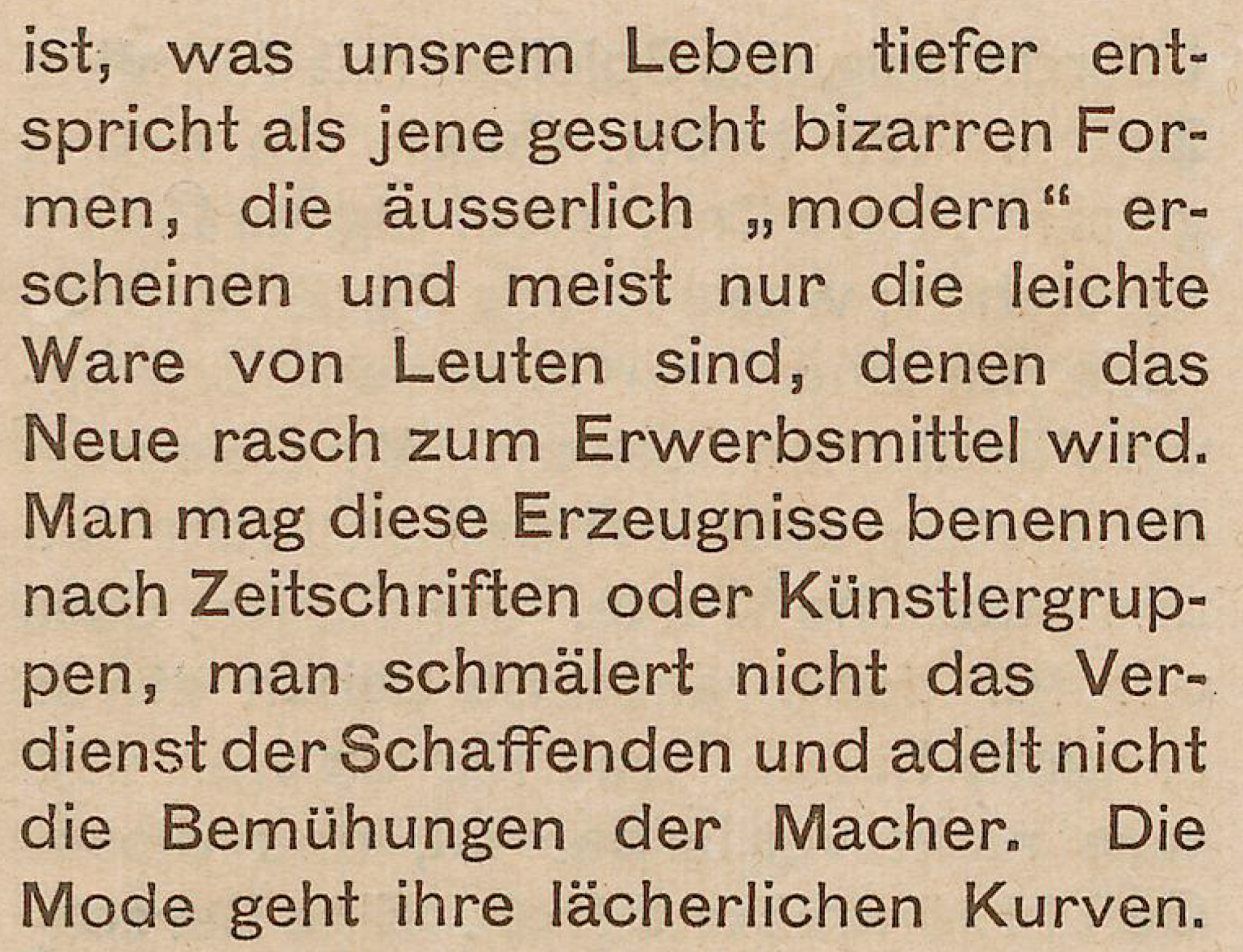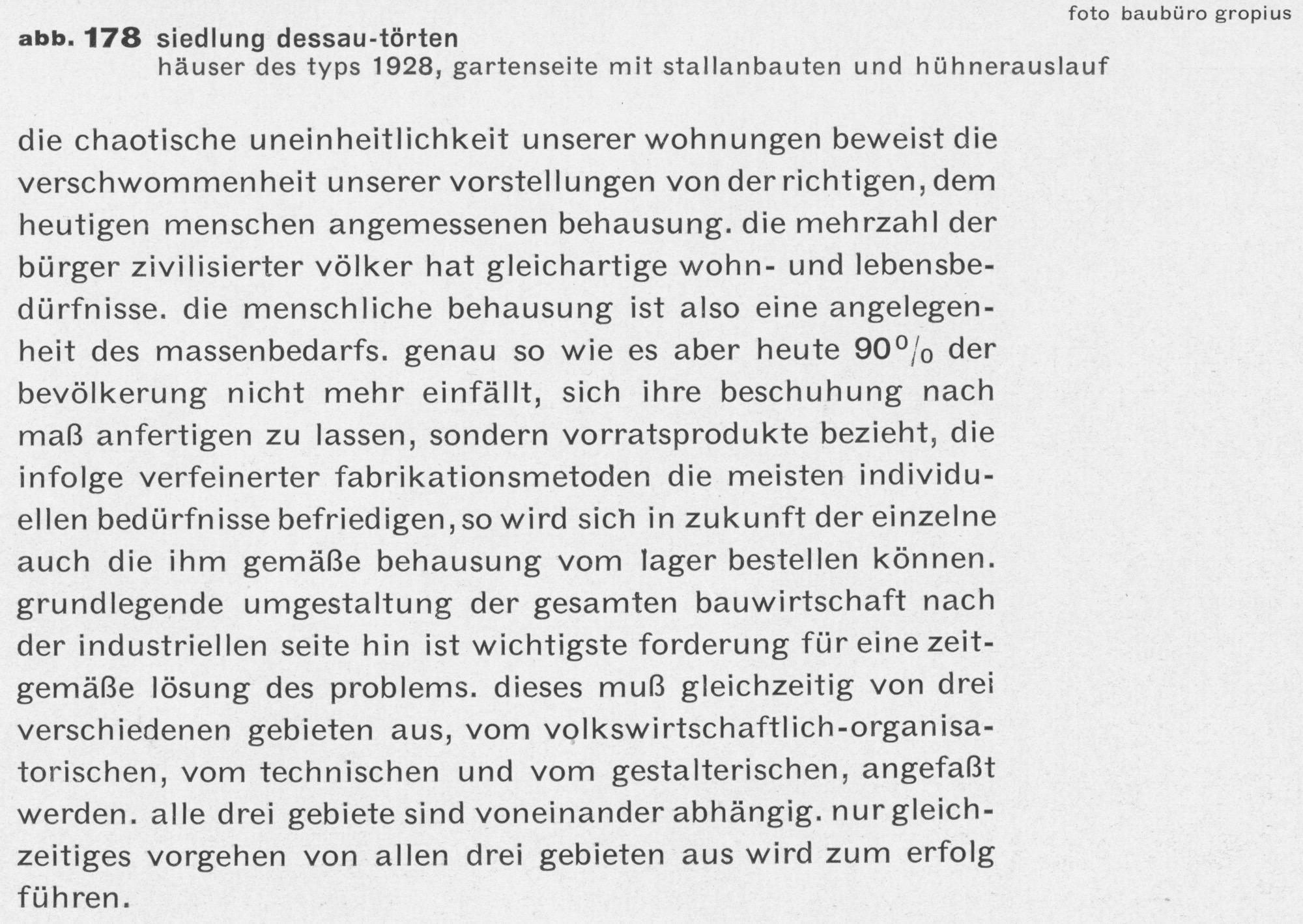
Schrift aus Bauhausbücher 12, 1930
Kann mir jemand sagen was dies für eine Grundschrift ist? und ob diese evtl. digitalisiert wurde?
ist aus dem Buch: «Bauhausbücher 12: Walter Gropius, bauhausbauten Dessau»
gedruckt: 1930
erschienen im Verlag: Albert Langen Verlag München
druck: Hesse & Becker, Leipzig
Ich kann leider nicht sagen welche Schrift es ist aber es ist mit Sicherheit nicht die Akzidenz Grotesk. Allein das »g« passt schon nicht – von den Strichstärkenunterschieden bei etlichen anderen Lettern (a, b, c, …) ganz zu schweigen.
Diese Schrift war eine sehr gängige »anonyme« Schrift zu der Zeit. Die wurde vermutlich in den 1870er Jahren aus Großbritannien importiert. Bei mehreren deutschen Schriftgießereien hieß die Schrift Breite Grotesk. Aber nicht alle Schriften aus der Zeit, die Breite Grotesk hießen, ließen sich auf diesem Entwurf zurückgehen. In etwas zwei Stunden poste ich eine Liste von den Schriftgießereien, die diese Schriften im Angebot hatten. Vielleicht könntet ihr dann eine Probe im Netz finden. Eine digitale Version dieses Entwurfs (anders als die andere breite Groteskschriften von Schelter & Giesecke) gibt es leider nicht.
Eine digitale Version dieses Entwurfs … gibt es leider nicht.
Schade, die hat nämlich wirklich Charme.
Die Schrift aus dem Bauhaus-Buch ist dieselbe (oder eine nahezu identische Kopie für eine Satzmaschine) wie die Schrift, in dem Peter Behrens’ Buch Feste des Lebens und der Kunst: eine Betrachtung des Theaters als höchsten Kultursymbols (Darmstadt, 1900). Anbei ein weniger-tolles Foto von ein paar Zeilen aus Behrens’ Buch.
Meine Vermutung ist, dass Ludwig & Mayer in Frankfurt die erste deutsche Gießerei war, die diese Schrift in Deutschland anbot (sie entwarf die jedoch nicht). Sie nannte die Schrift Breite Grotesque. Wilhelm Woellmer’s Schriftgießerei in Berlin hatte das Design auch (unter der Name Breite Grotesk). Woellmer war jedoch aber nicht die Firma, die sie ursprünglich herstellte. Wie oben geschrieben vermute ich, dass die Schrift in Großbritannien »geboren« worden ist; deutsche Gießereien hätten Matrizen davon bekommen, entweder in dem sie Matrizen von denen gekauft haben oder sie über die Galvanoplastik geklauten. Es kann sein, dass die genaue Situation von Firma zu Firma sich unterschied.
Als Quelle Tippe ich auf Miller & Richard (also ihre Grotesque, No. 1), wobei die Gothic No. 9 von der Cincinnati Type Foundry in den USA sehr ähnlich aussieht und ich habe keinen grundlegenden Vergleich gemacht. Vielleicht kam sie von Cincinnati an Miller & Richard oder anders herum.
Woellmer machten sogar weitere Schriften, die im selben Designstil waren. Also bauten sie daraus eine kleine »Familie« mit halbfett, eine schattierte Version, die schattierte Version für dem zweifarbigen Druck usw. (einige Bilder davon kommen in meinem Vortrag hier auf; ansonsten hat Ralf vielleicht Proben von diesen Schriften in Weimar).
Ansonsten in Deutschland boten Brüder Butter in Dresden sowie J. John Söhne in Hamburg die ursprüngliche Schrift an. Beide Firmen verkauften sie ebenfalls als Breite Grotesk. Monotype machte das Design auch für ihren Setzmaschinen (als Monotype Grotesque 51 bzw. Series 51, leider nicht mit den anderen Monotype Grotesque varianten digitalisiert). Ich habe dunkel in Erinnerung, dass die deutsche Tochtergesellschaft der Mergenthaler Linotype Co. die Schrift in den Jahrzehnten vor dem 2. Weltkrieg ebenfalls für ihre Maschinen angeboten hat. Vielleicht sogar Intertype under anderen Setzmaschinen-Firmen aus dem frühen 20. Jahrhundert.
Zumindest das schöne t
r und g sind auch sehr schön – das a finde ich allerdings ein bisschen zu "swiss".
Dann werfe ich mal noch diese beiden in die Runde – da ist das a weniger geschlossen, dafür passen dann aber viele andere Merkmale (z.B. die Strichstärken-Dynamik) weniger gut: